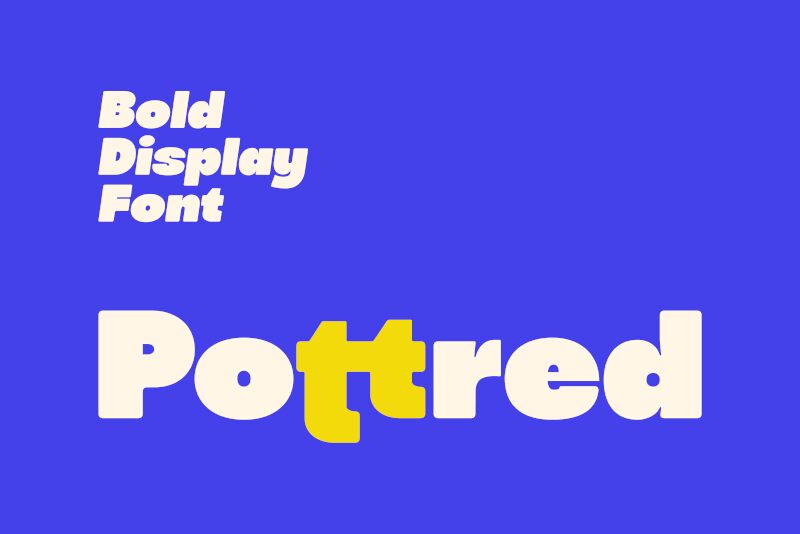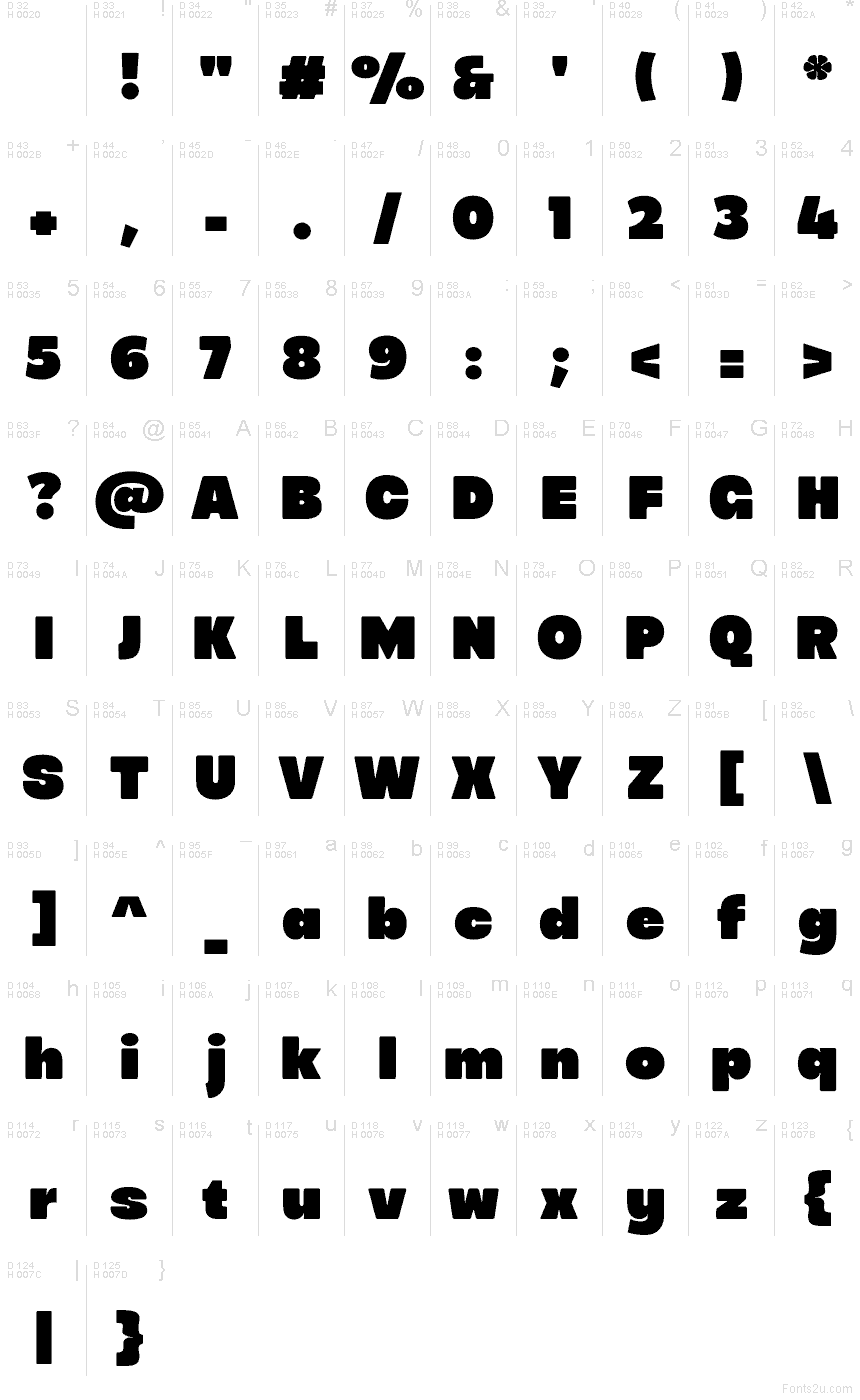
Pottred, da Glyphminds Studios, é uma fonte sem serifa, ultra-negrito, arredondada e gratuita, com um visual suave e inflado que parece mais lúdico do que sofisticado. As letras são construídas com formas robustas, quase como pílulas, com curvas amplas e junções rombas que mantêm o ritmo compacto e amigável.
Isso torna esta fonte gratuita uma escolha natural para embalagens de lanches, branding infantil, títulos de pôsteres, telas de abertura de aplicativos e logotipos curtos onde uma silhueta grande é mais importante do que detalhes minuciosos. Ela também se adapta bem a capas e títulos, pois essas formas pesadas e arredondadas se mantêm unidas como blocos ousados com um tom alegre, quase como um brinquedo.